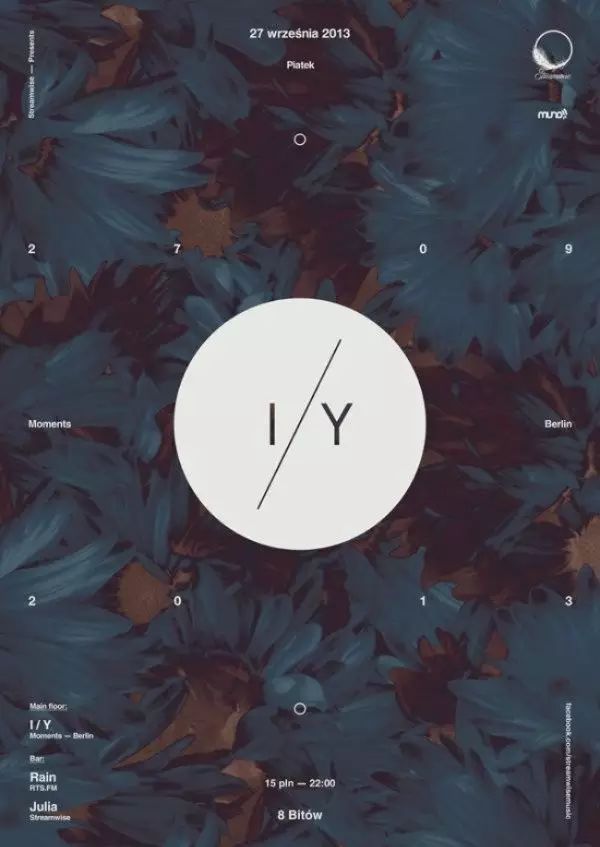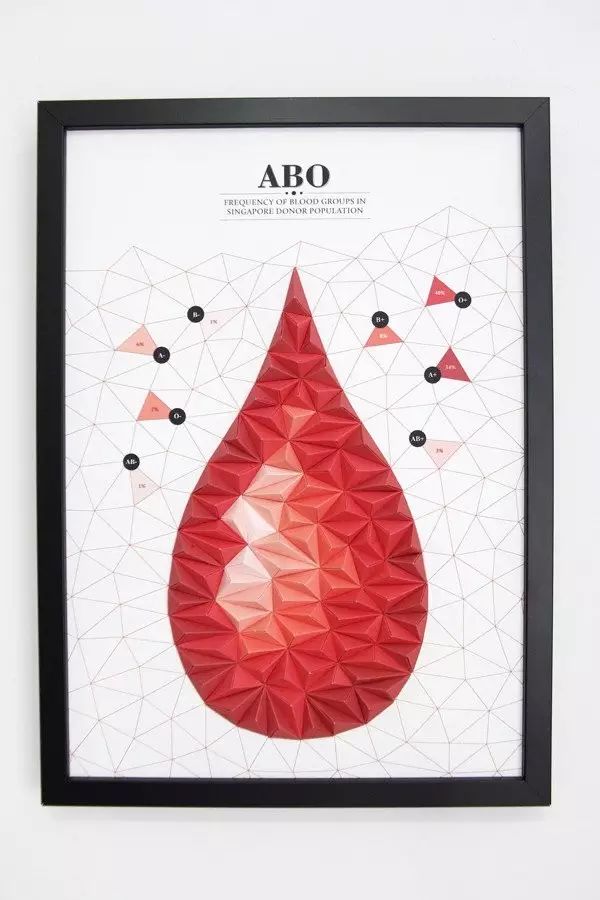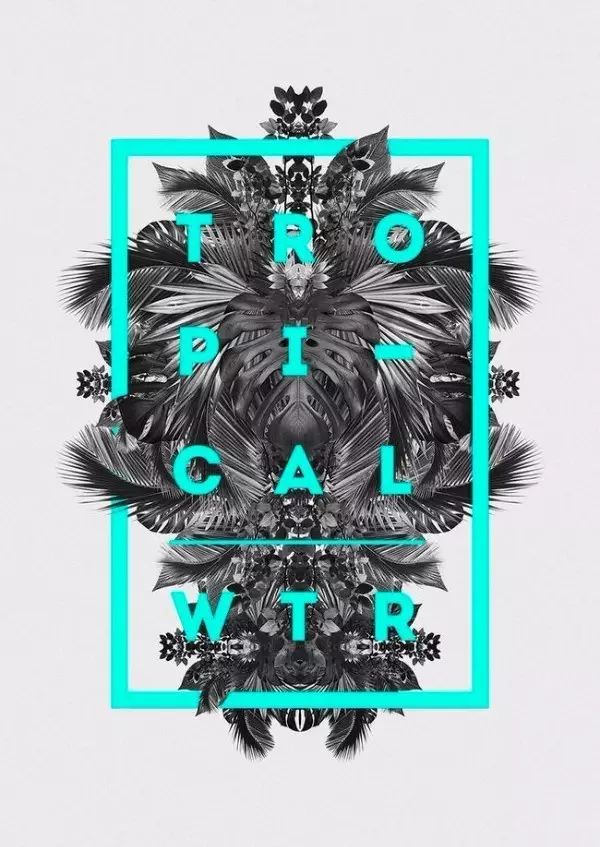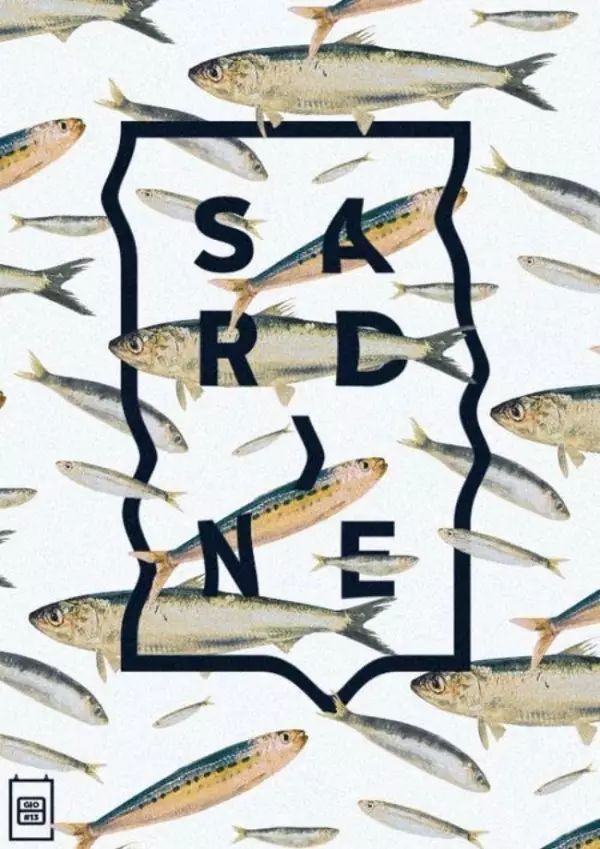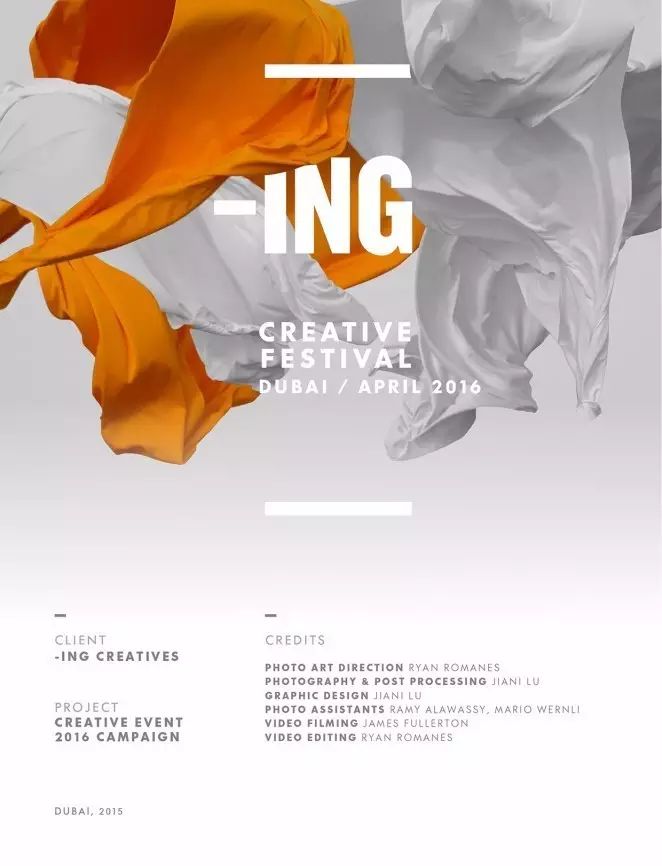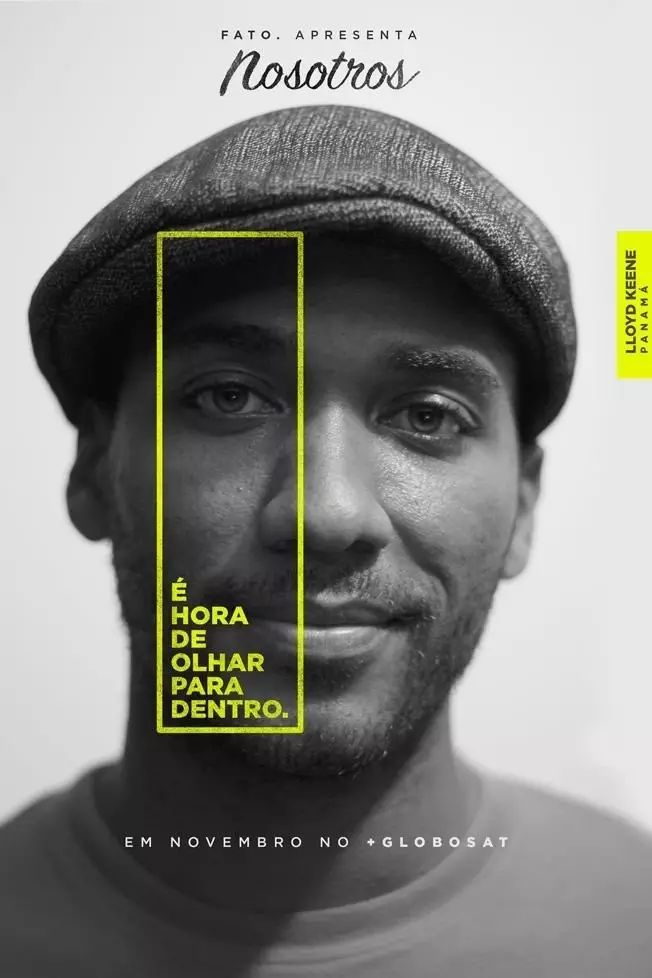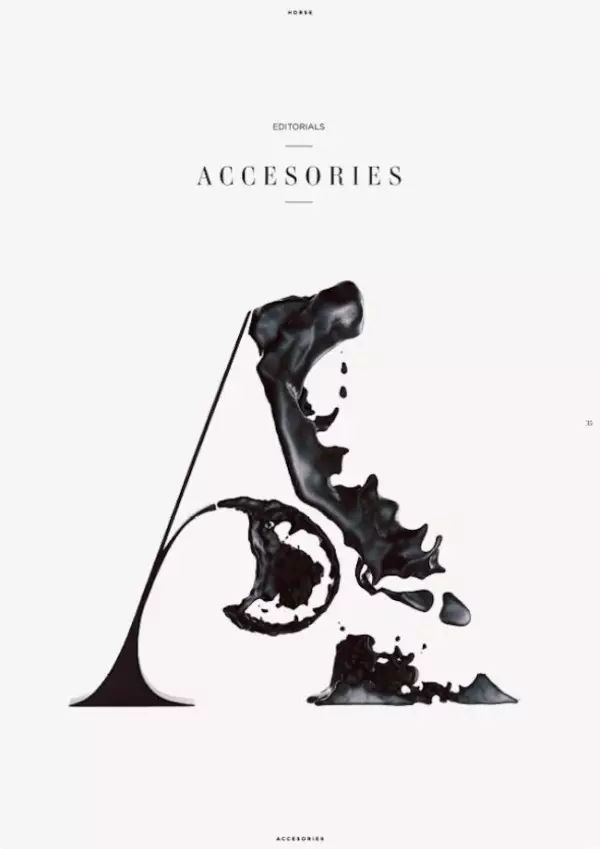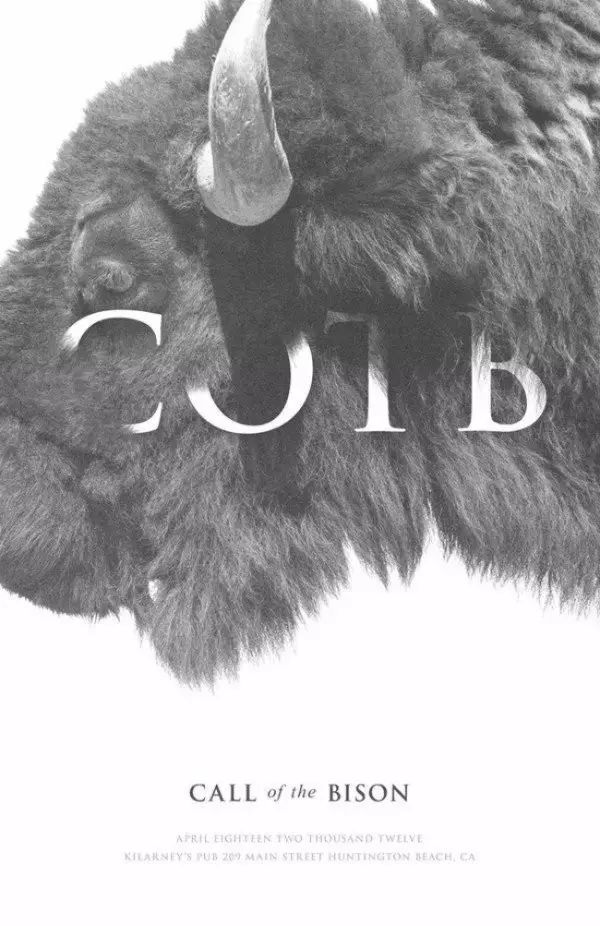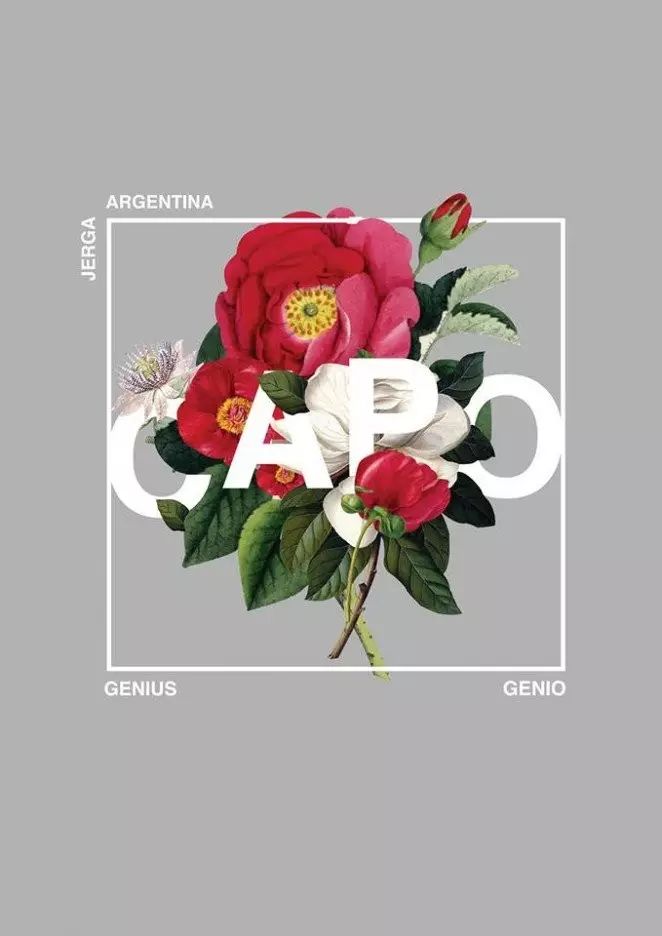
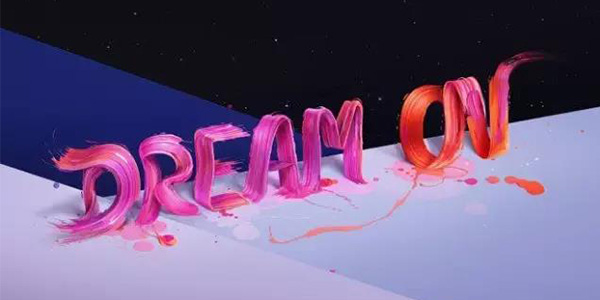
平面设计 | 质感和纹理在视觉表现中扮演着什么样的角色?
今天与大家分享,如何在平面设计中创意性地使用好质感(Texture)?每种应用分别具有什么样的效果,各自特点是什么?希望对大家的平面设计甚至作品集创作有所帮助。
| 纹理&材质 |
平面设计中,有一个词经常被提及,就是Texture.
Texture在平面设计中包含的意思很广泛,它可以是指材质、也可以指特殊的纹理,但无论是材质还是纹理,所具有的独特质感都可以对视觉产生丰富的刺激。不仅可以让视觉冲击变得更加丰富,还能起到对视觉焦点的衬托作用。
| 质感の重要性 |
五官的存在让我们可以多元化地去拥抱这个世界,感受万事万物丰富的细节。
就像色彩让视觉感受不再单调一样,质感的存在本身也让我们更直观地去理解一件东西的质地。
试想,同样让用手接触浆洗过的麻质布料和光滑透软的真丝布料时,感受一定非常不同;在浴室,触碰涂满全身的肥皂泡亦或是头发触碰到肩头的时候,我们知道,理解这个世界,质感唤醒的触觉就是最直观的一种方式。
而在平面设计中,质感需要转化一个维度,以2D的平面呈现,却同样肩负着唤起人们感知的作用,不仅如此,利用质感本身与视觉符号与元素的结合与平衡,可以起到很多意想不到的效果。
| 平面设计中の质感应用 |
自然质感做底,营造熟悉感
强调质感(texture),最常用的方式之一就是直接将自然材质的纹理应用于平面设计中。比如,自然元素中提取草地中鲜嫩多汁的一簇经过PS调色与规模的累加之后应用于设计中,或者如下图所示,将羽毛的轻柔质感直接拿来应用。
引入自然质感的最明显的好处就是世界上可供应用的自然元素实在太多了,简直就是天然的宝库。并且,因为是自然元素的关系,很自然地能够唤起人们的熟悉感,让人觉得更加温暖、亲切、生动。
在上面的海报中,设计师Dawid Sieradzki就将自然质地与极简风格字体搭配在一块,创造了丰富、有机的氛围。运用花朵的质地和反色的色调,这种常规与反常规的结合,更加抓人眼球。与此同时,白色圆形的轮廓处于整体居中位置,成为视觉焦点。
Tips:自然背景做底,相应与更加吸引眼球的前景做搭配。
上面这个例子中, Keith Barney将自然的纹理与图形元素交织在一起,得到一个amazing的海报设计。同样的效果(文本与背景交织的技法),还可以应用在植物摄影作品中。
植物摄影作品与字体设计之间的交织搭配案例。案例中的字母利用了视觉错位的效果,好像彼此之间并不在一个平面,有一定的3D景深效果。
人工设计纹理,营造熟悉感
人工设计纹理,不像自然纹理,它更多地是为了营造超现实的氛围和痕迹。人工纹理质感既可以指诸如布料、皱纹纸、水泥墙等人造之物作为平面设计的底层效果;也可以指运用拼贴原理,截取自然纹理的效果,并且利用二方连续或四方连续做叠加,做出重复、三维等视觉效果。
人造刺绣布料作为平面设计的底层背景效果。
人工笔触效果,带给平面设计中的字体更真实的触觉和呼吸感。
使用实物纹理触觉挑逗视觉通感
与纯粹的视觉纹理做背景不同,实物纹理更多地侧重运用物理质感,营造与平面设计的背景不同的额外的视觉效果。实物做背景纹理的使用范围非常广泛,物理质感的引入也会特别地吸引眼球。这类设计通常在创作的过程中会引入超平面概念,即在三维空间进行创作,通过物品的排放、颜料的厚涂、立体拼贴等手段。
物理质感特别强调物质本身的自然属性,这种属性的加入为平面设计营造出特别的感觉。这种应用手段经常见于文具设计、包装设计或者杂志封面设计,因为某种程度上这样的设计更能加深人们的印象,并且创建视觉与视觉多冲感官的通感纽带。
上述就是典型的超平面设计,采用了颜料厚涂的方式,在平面设计中,创造出了额外的立体效果。在文字与背景色统一的情况下,正是利用了立体的触感,增添了视觉可辨识性。
利用物理质感本身也包含很多种方法,比如上面这个是来自Pierre Mendel的作品,就运用了纸张本身的皱缩感。
来自Siang Ching的作品,纸张凹凸的质感与原本是血液低落的形状结合,创造出独特的视觉效果。
质感与文字产生互动
运用具有质感纹理的背景与文字的互动结合,可以营造出具有沉浸式体验的视觉特征,这种方式可以更好地凸显景深和设计的细节。
文字与背景纹理的互动结合,灵感来自PKG Branding
Fabian De Lange的平面设计非常精致,设计师出色地将平面设计元素互相交织在一起。
MUMBAI的平面设计则是使文字和背景中具有3D效果的树叶融合在一起,简单的处理即可使得画面在清新之余,利用景深和三维立体效果营造了优秀的视觉体验。
摄影作品完成质感背景的华丽转身
在所有凸显质感的平面设计手法中,摄影也是常见的方式之一,同学们千万不要忽略这么好用的方法。摄影的好处在于,首先它能就地取材,省去了很多创建背景的麻烦,因为被拍摄的肌理是现成的;其次是摄影方式门槛较低,同学们可以在初期用手机尝试拍摄和创作。
来自Matthem Metz的作品就是个很好的例子,完美利用摄影的原生态作品做纹理背景,字体色彩与背景并没有采用高强度的对比,而是故意采取了若隐若现的视觉效果。
另外一个例子,来自设计师Alejandro Pereira,具有超强纹理效果的摄影作品与白透明蒙版前景做结合,这种利用半透明蒙版镂空效果,不仅使得背景抢眼,同时还能兼顾前景中文字的可读性。
与Alejandro的设计中利用半透明蒙版营造的朦胧效果不同,Nostros project在背景中为文字选取了一个亮色,视觉上更加跳跃,能够第一时间将人的目光集中吸引。这也是很多杂志封面特别惯用的一个文字与背景结合的手法。
用变形字体创建引人注目的艺术效果
富有质感的纹理与文字的整合打包应用也相当惊艳,并且可以组合出多种多样的视觉效果。比如纹理与字体的变换,纹理与字体色彩的结合应用等等。
在平面技法的综合表现中,将3D转化运用到2D创作中是非常常见的做法。比如Eren Saracevic的设计就将3D泼墨效果与字体结合,运用到了2D的平面设计海报中。
纹理与文字结合的手法还有一种,就是直接将纹理做成文字,一般这样做都会呈现出镂空的效果,这就要求与背景呈现出比较强烈的色彩对比,并且采用纯净的背景色。